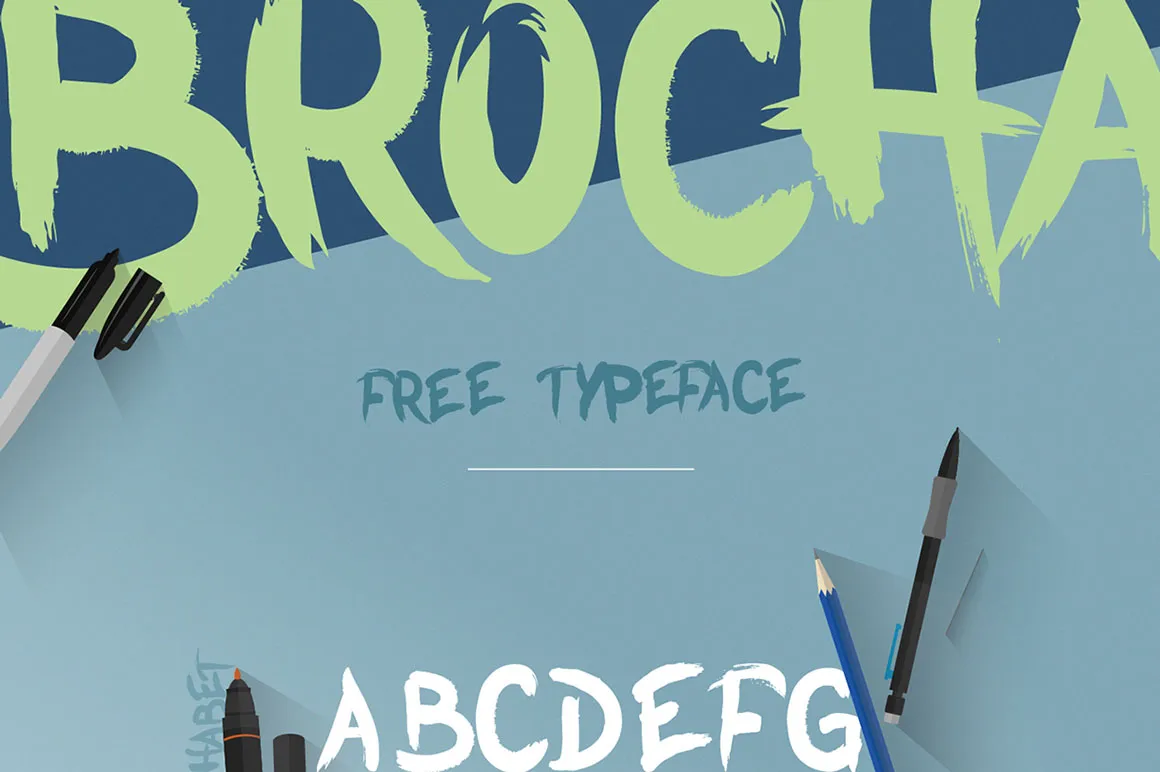
BROCHA – Free Typeface – Fonte Grátis
BROCHA - Free Typeface
A fonte ‘BROCHA’ – uma seleção livre e única do designer Hamilton – é perfeita para artistas e criadores que desejam adicionar um toque autêntico à suas obras de arte. Inspirada no uso de pincéis, esta fonte script está disponível em versões gratuitas para uso pessoal, o que a torna uma opção muito atrativa para quem busca personalizar seus projetos gráficos com estilo sem gastar dinheiro extra. Convidamos você a explorar essa fonte única e poderosa. Ela oferece um gosto refinado de liberdade criativa e permite que sejam expressadas as mais sutis nuances de sua arte. Não importa o tipo de projeto – seja uma arte digital, uma ilustração ou até mesmo um design de site – a ‘BROCHA’ pode adicionar profundidade e personalidade ao seu trabalho. Com suas linhas elegantes e detalhes cuidadosamente criados, ‘BROCHA’ se destaca no cenário dos recursos gráficos. Este é o tipo certo para aqueles que buscam uma fonte que ofereça tanto a liberdade quanto a precisão necessárias para criar um trabalho de alta qualidade.